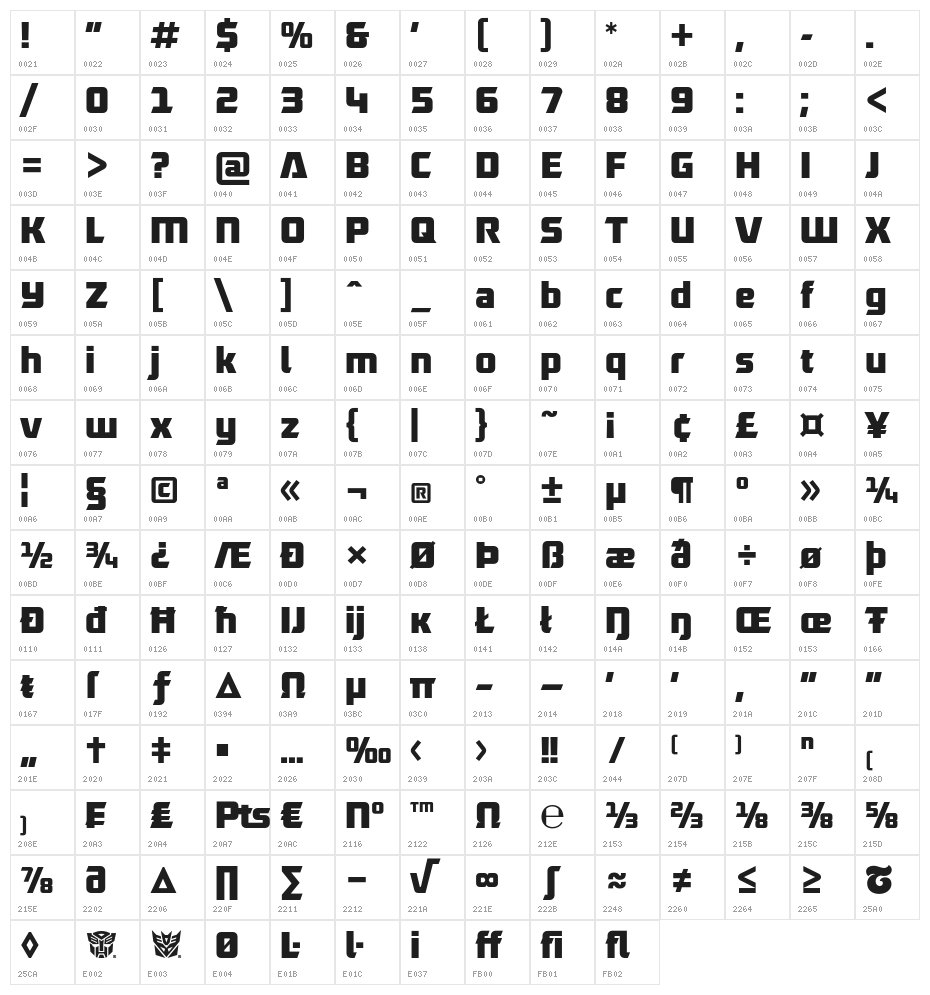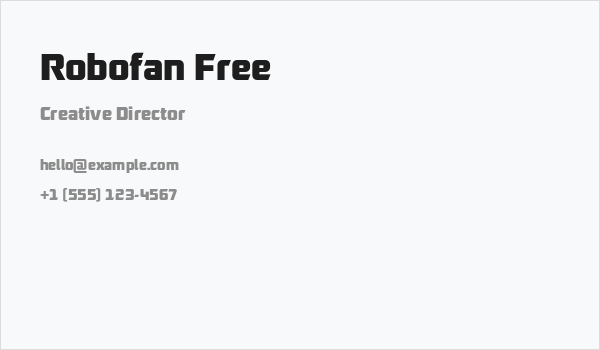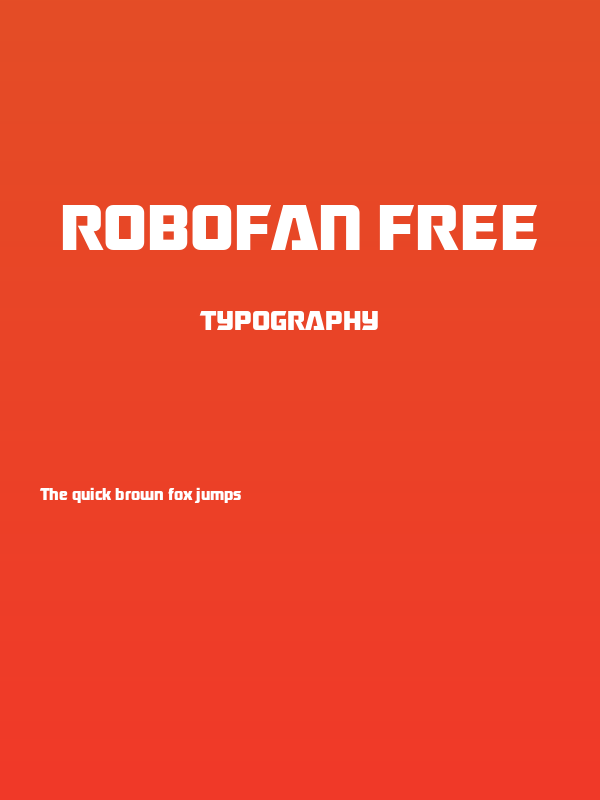
Robofan Free Font
✎ Futuristic
| 推荐项目 | Ideal for technology branding, video game titles, posters, and any project requiring a modern, impactful typeface. |